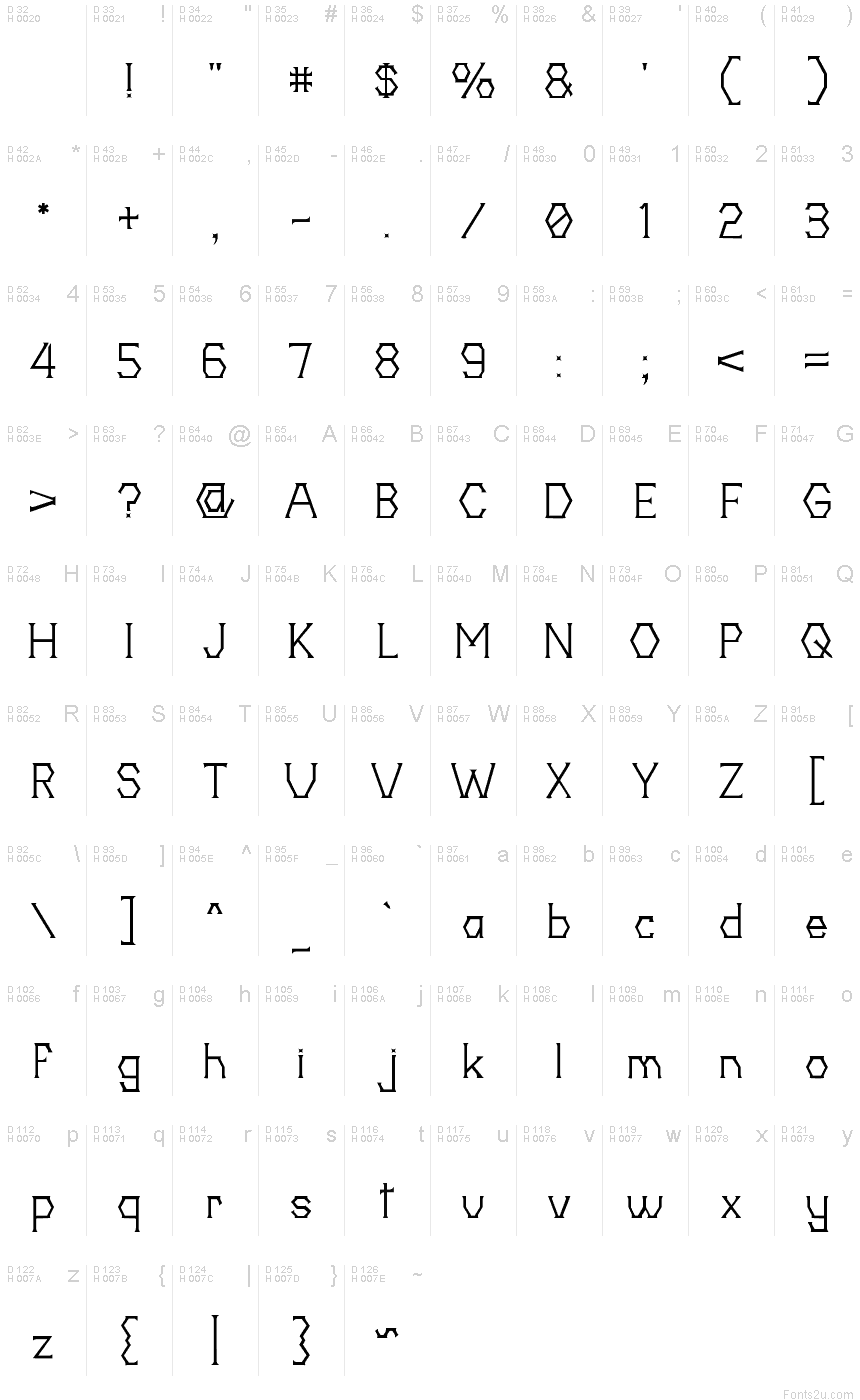
يُعد 20th Centenary Faux خطًا استعراضيًا جذابًا يفيض بسحر كلاسيكي (ريترو). تضفي حروفه الهندسية الجريئة طابعًا عتيقًا، مع حواف حادة ومميزة وجمالية لعوب تكاد تبدو مصممة يدويًا.
تتجلى مرونة هذا الخط في كونه خيارًا متعدد الاستخدامات لمجموعة واسعة من تطبيقات التصميم، بدءًا من العناوين والشعارات اللافتة للنظر وصولًا إلى تصميم العلامات التجارية والتغليف ذات الطابع الحنين إلى الماضي.
يمزج الأسلوب المميز لخط 20th Centenary Faux بسلاسة بين الماضي والحاضر، مما يمنح المصممين أداة طباعية فريدة لإنشاء عناصر تصميم بصرية مذهلة لا تُنسى.
20th Centenary Faux